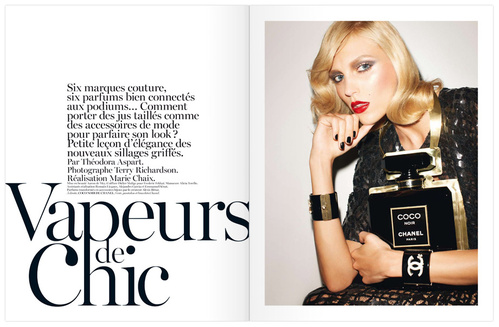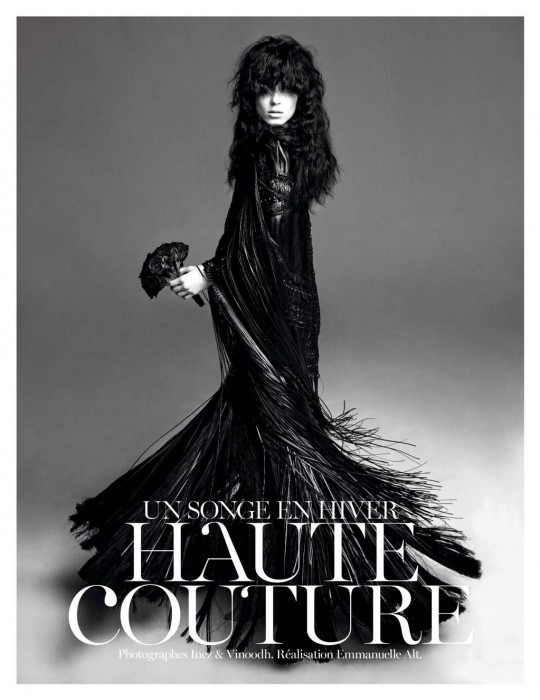
Schriftzug Cover: HAUTE COUTURE
hat vielleicht jemand von euch eine Idee welche Schrift hier verwendet wurde???
Miller Banner?
Die Vogue hat die gesuchte 2012 schon verwendet, aber solche Alternativformen hab ich noch nicht gesehen.
found this comment in another forum:
It's is actually a customed Miller font for VOGUE, it's called MBVogue
If you're looking to replicate the uppercase C from the magazine, my best guess is they 'designed' a new letter by combining the normal uppercase C with the drop end of an enlarged lowercase C.
Dann lag ich mit der Miller Banner als Basis ja gar nicht so falsch :-)